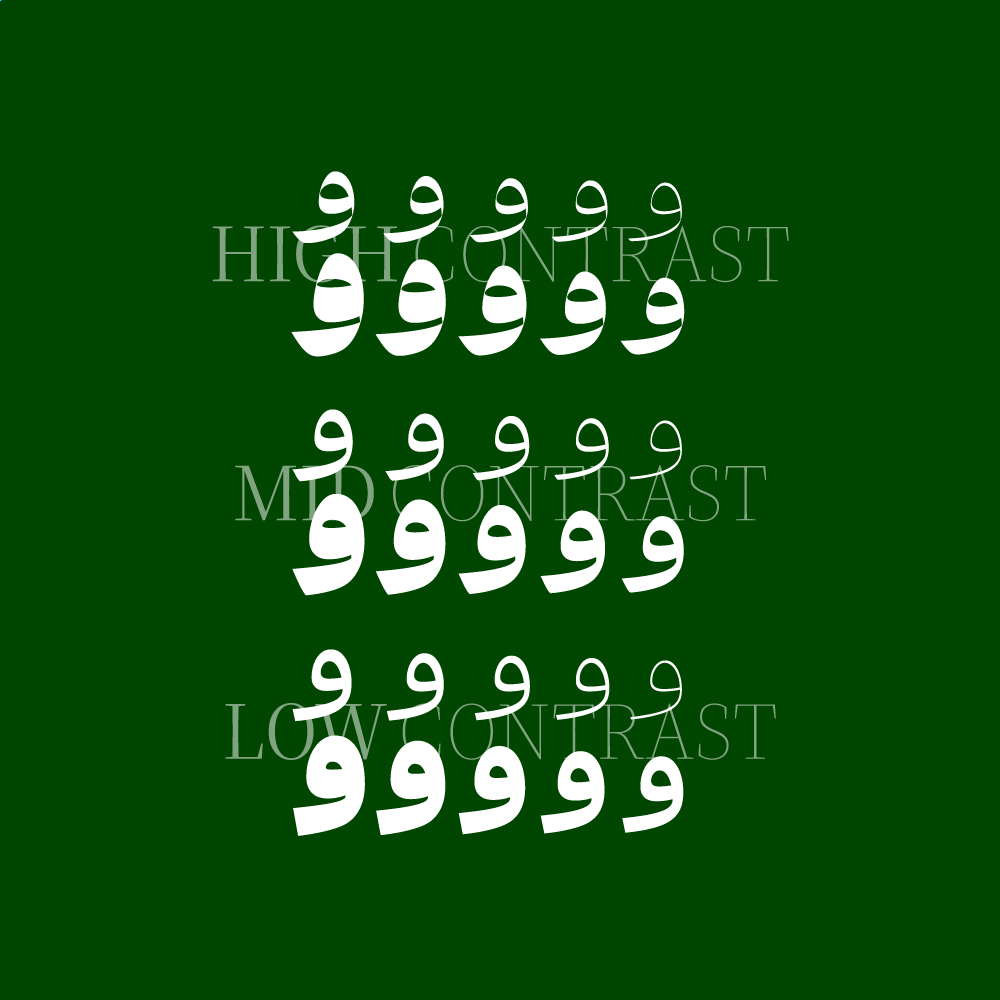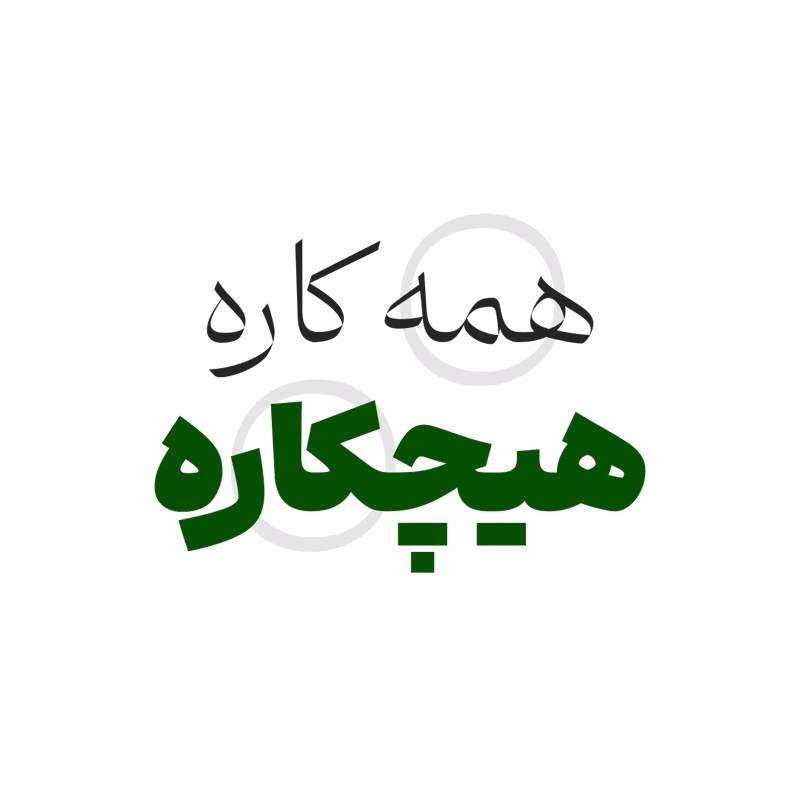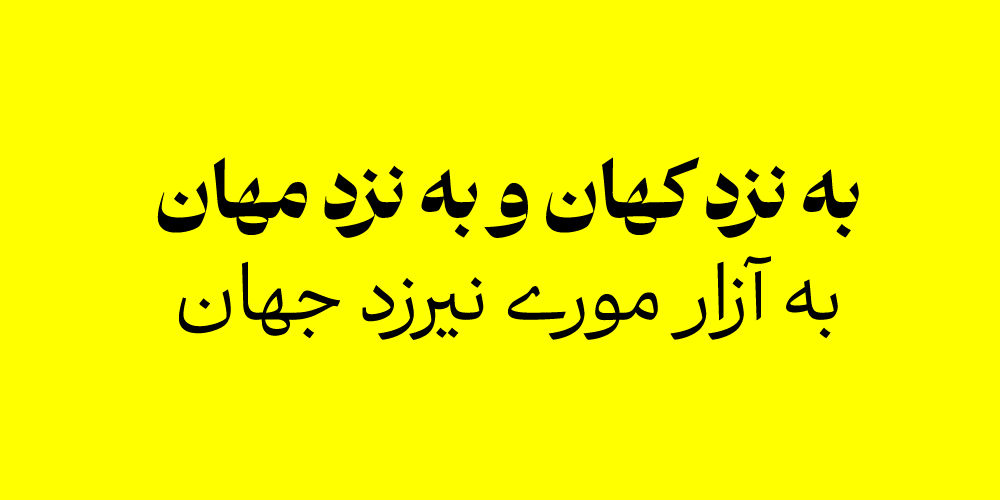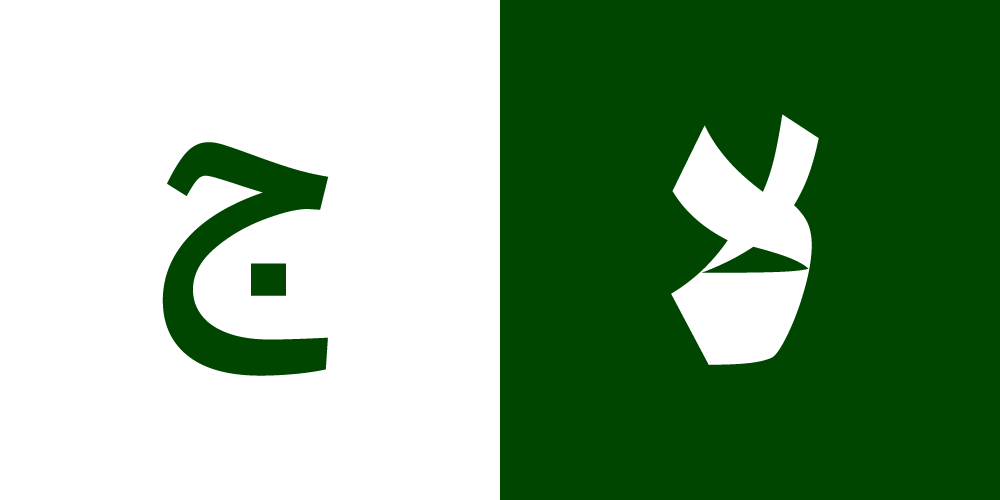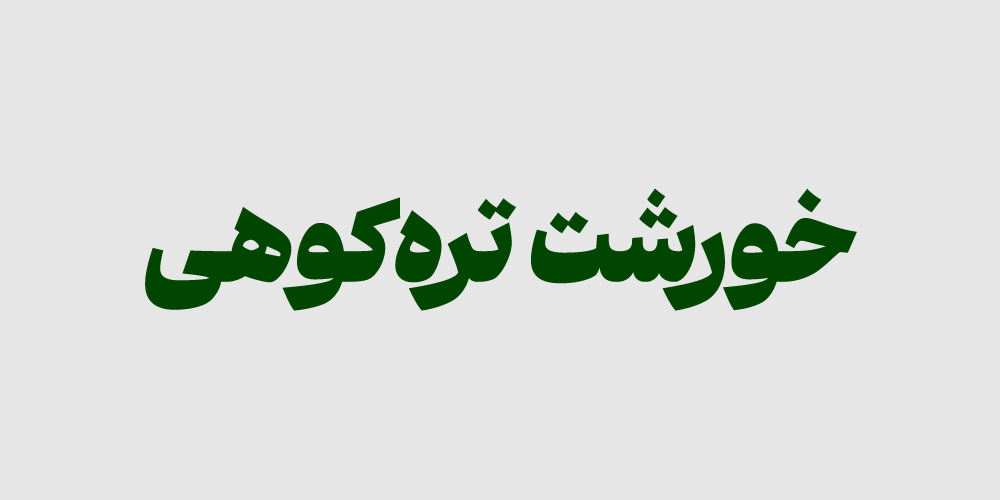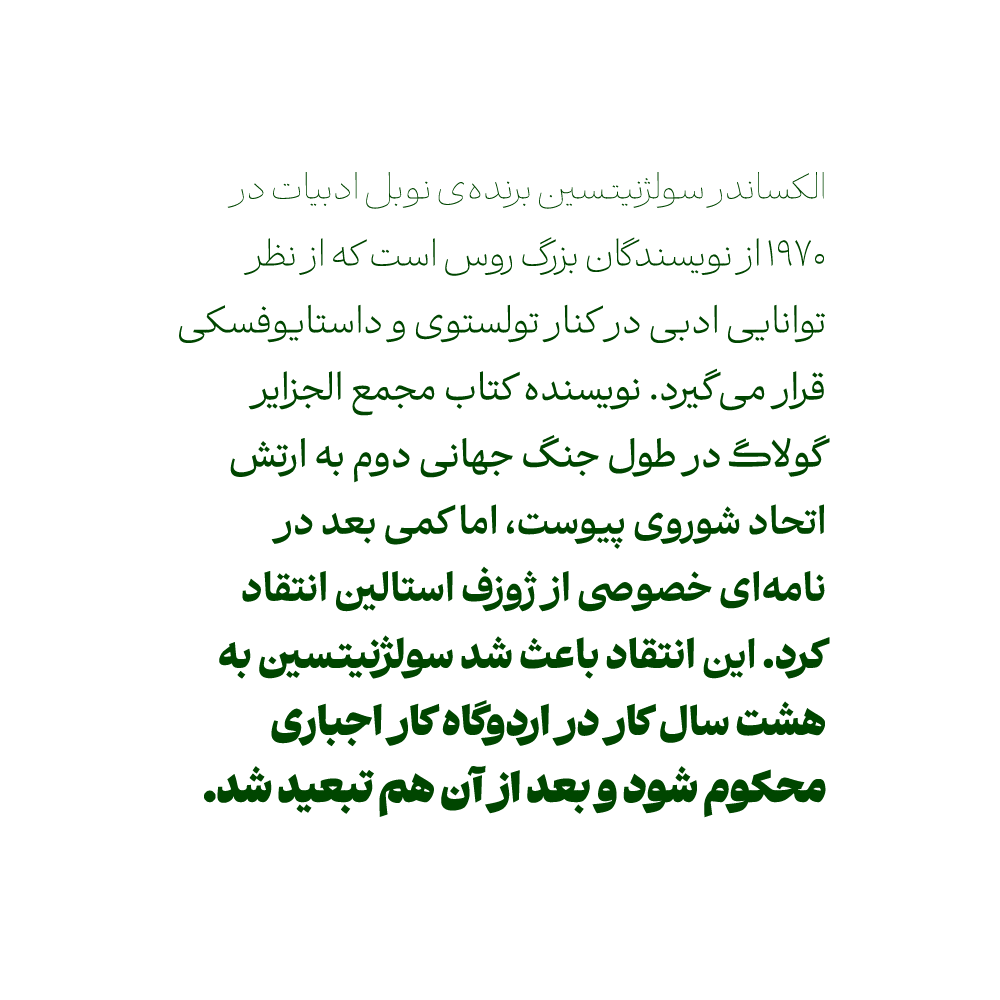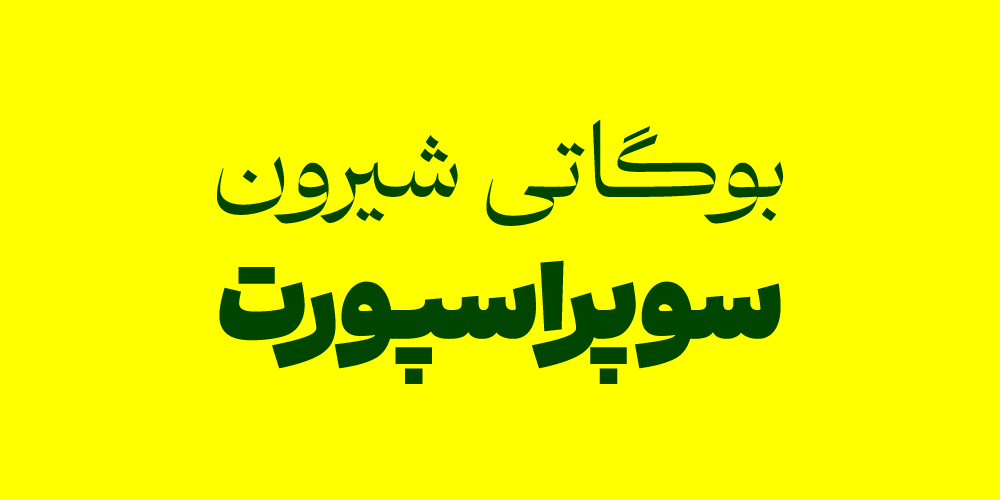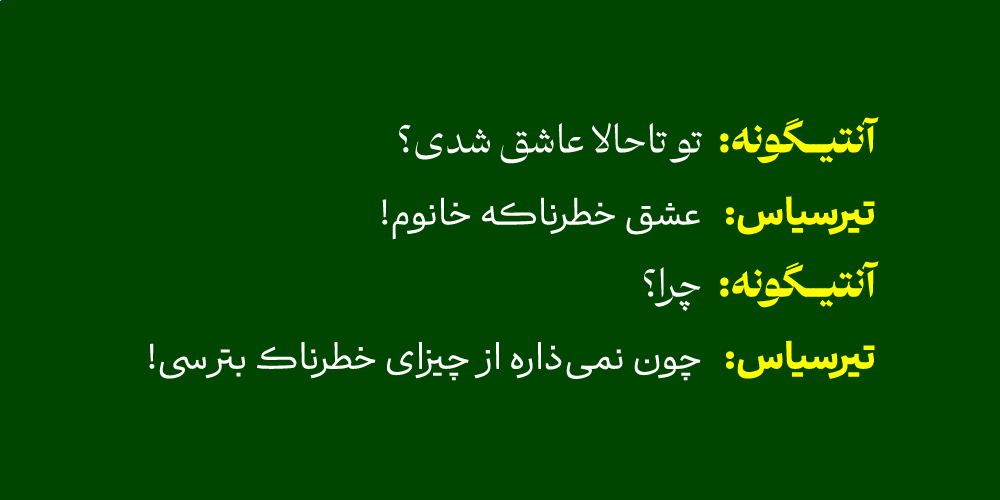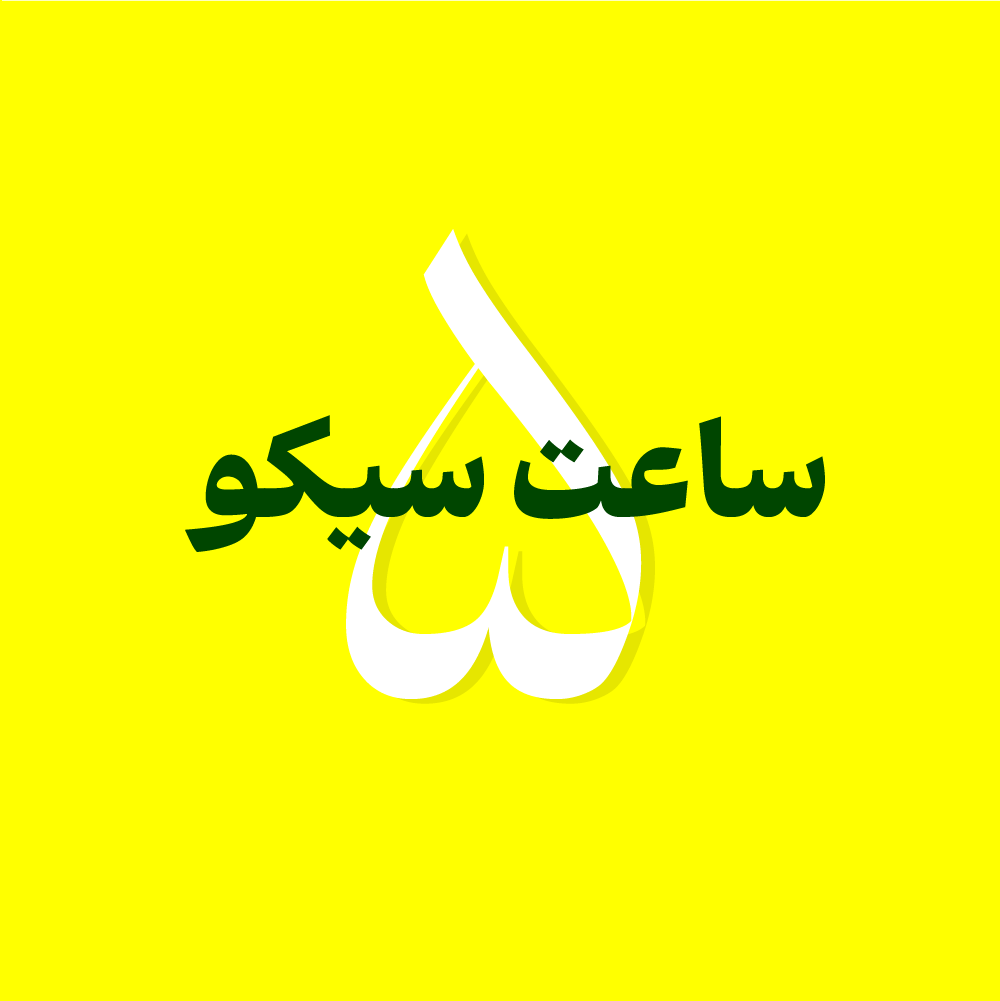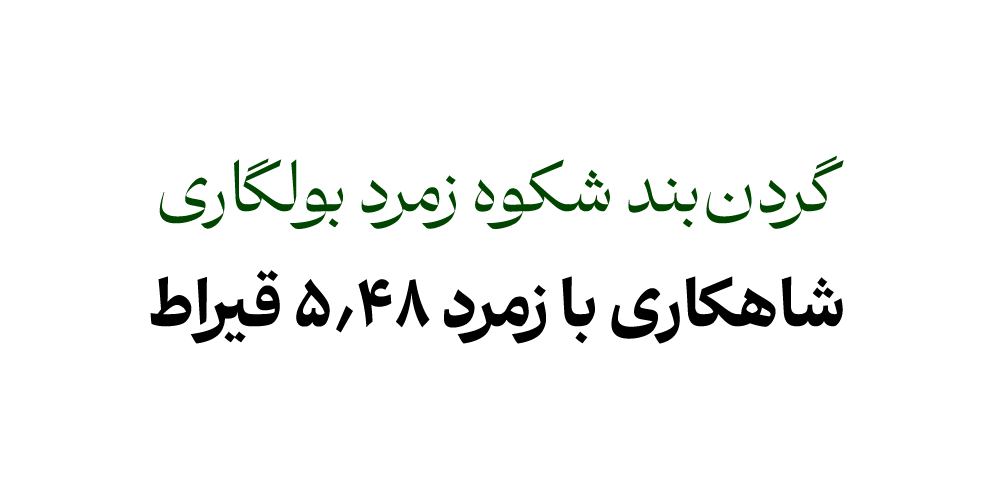
تنوع وزنها در فونت ابَر
فونت ابَر دارای ۱۰ وزن (Thin, ExtraLight, Light, Regular, Medium, SemiBold, Bold, ExtraBold, Black, ExtraBlack) و ۳ سطح کنتراست (Low, Mid, High) و نسخهی وریبل است.
امکان همعرض کردن اعداد
با فعال کردن گزینهی Tabular Numbers همهی اعداد با هر وزن و زبانی همعرض میشوند. این امکان برای جدولنویسی و حسابنویسی بسیار کاربردی است.
ریال و تومان
با فعال کردن Stylistic Sets 2 میتوانید نمادهای اختصاصی ریال و تومان را فعال کنید و نمادهای ریال عربستان و درهم امارات با Stylistic Sets 3 در دسترساند.
چندزبانه
ابَر از زبانهای فارسی، انگلیسی، عربی، اردو، کردی و جاوی پشتیبانی میکند
ترکیبات و حروف جایگزین
ابر دارای ترکیبات (Ligature) و حروف جایگزینی (Alternative) است که تاثیر بسیاری روی زیبایی نوشته میگذارد.
تراز عمودی اعداد
با فعال کردن Stylistic Sets 4 میتوانید تراز عمودی اعداد، علائم مرتبط و نمادهای پولی را تنظیم کنید.
تفاوت الگوی دیزاین هر سبک
فونت ابر در کاربرد